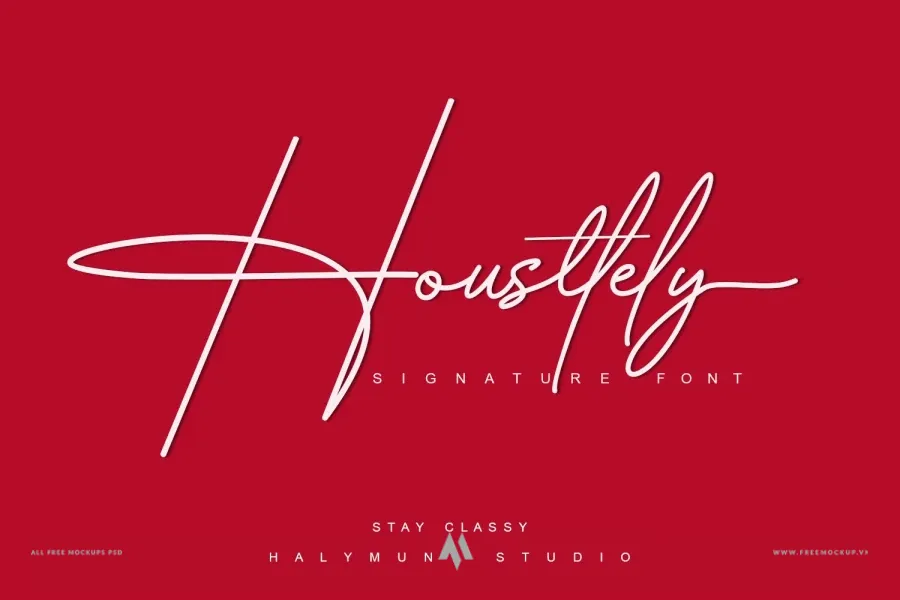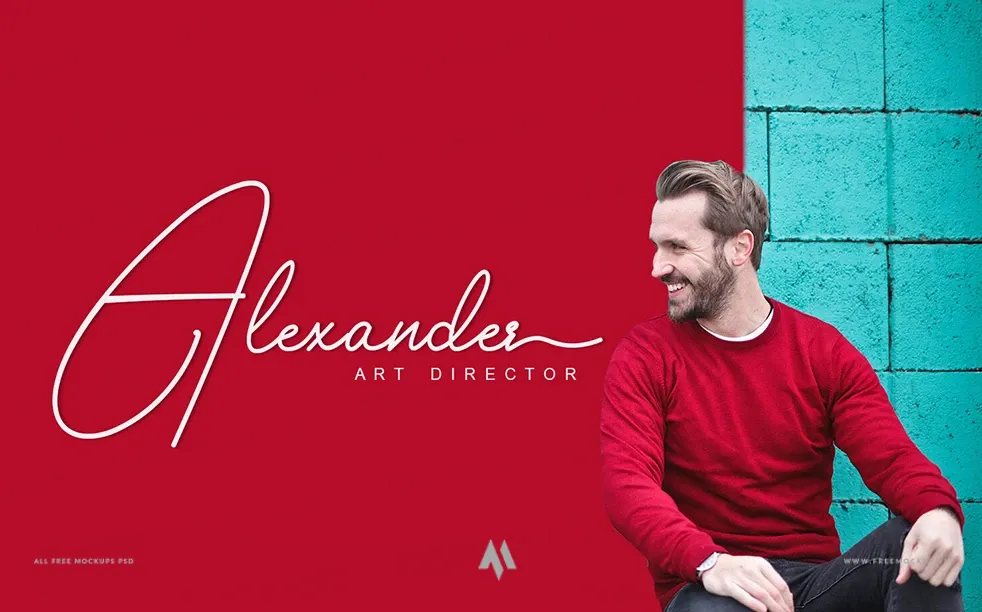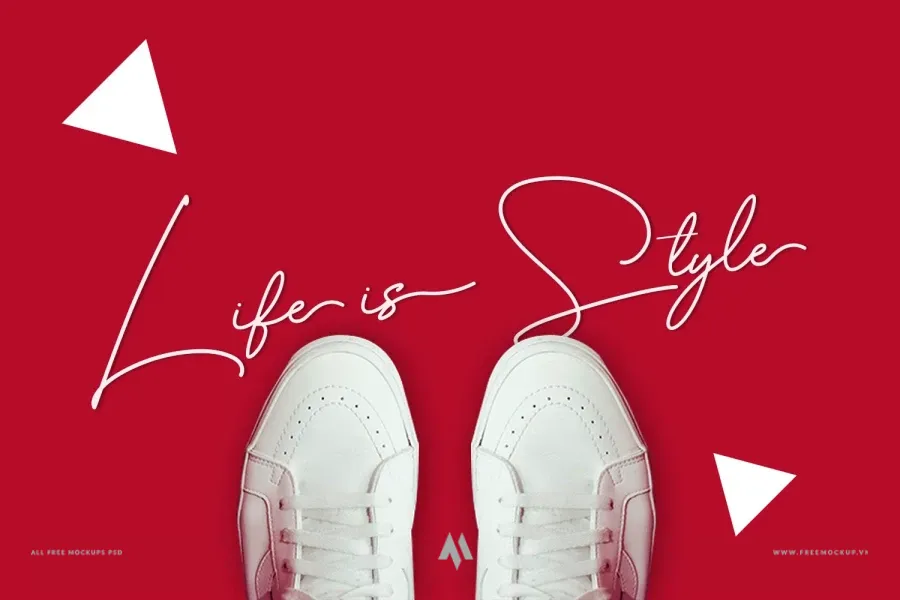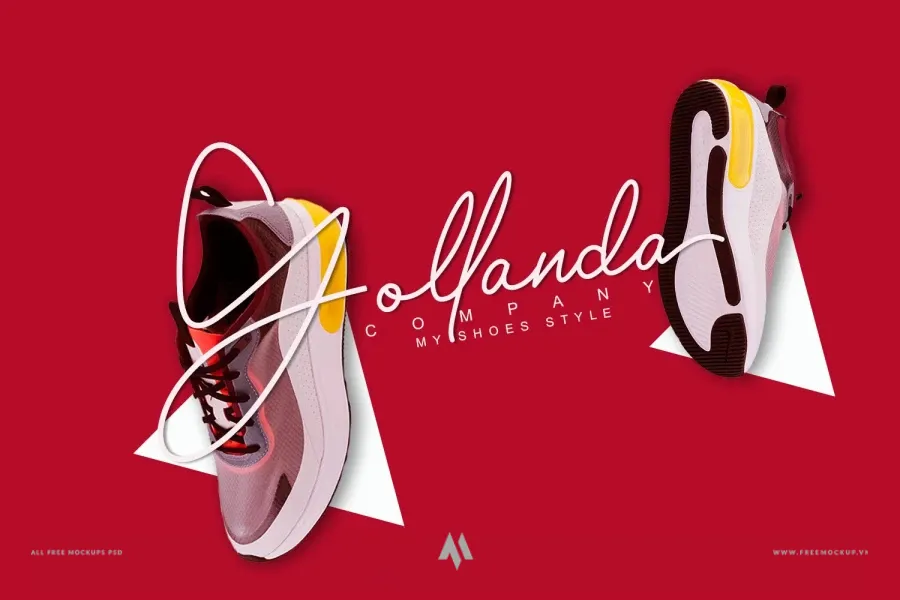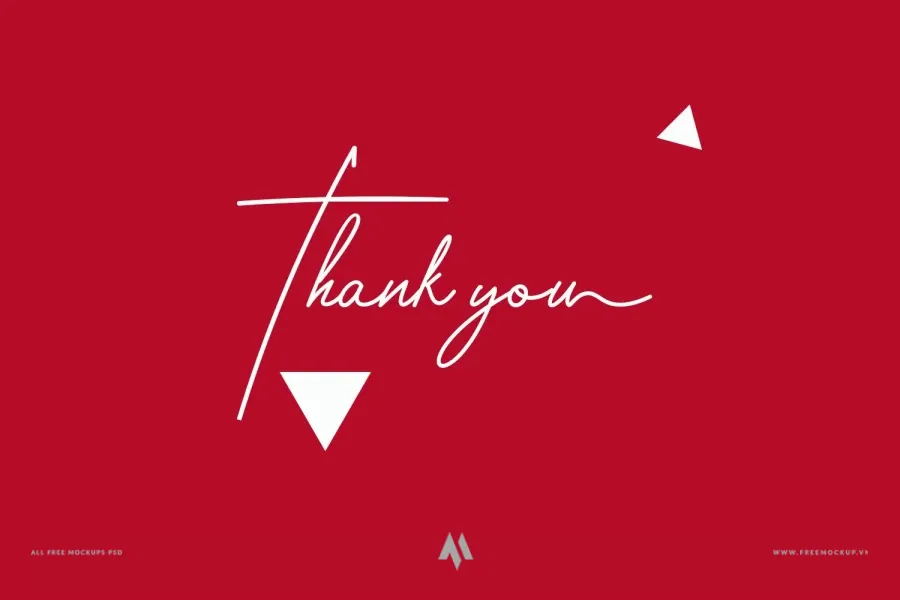
Housttely Signature Việt Hóa là bộ font chữ ký đơn nét (Monoline Script) mang phong cách viết tay hiện đại, tinh tế và đầy cuốn hút. Với những đường uốn lượn mềm mại, độ dày nét đồng nhất cùng dòng chảy tự nhiên, bộ font mang đến vẻ đẹp thanh lịch, sang trọng và đậm dấu ấn cá nhân cho mọi ấn phẩm thị giác cao cấp.
Đặc điểm nổi bật
- Phong cách Monoline thanh thoát: Nét vẽ đều đặn, liền mạch tạo cảm giác chữ ký tay chân thực, phóng khoáng và chuẩn mực.
- Tối ưu hiển thị & Tự nhiên: Từng ký tự được cân chỉnh nhịp nhàng, giúp các từ ghép nối mượt mà như chữ viết tay thực tế.
- Chuẩn hóa tiếng Việt hoàn chỉnh: Hệ thống dấu tiếng Việt được trau chuốt tỉ mỉ, đồng bộ với phong cách nét ký mảnh mai mà không làm gãy nét hay rối mắt.